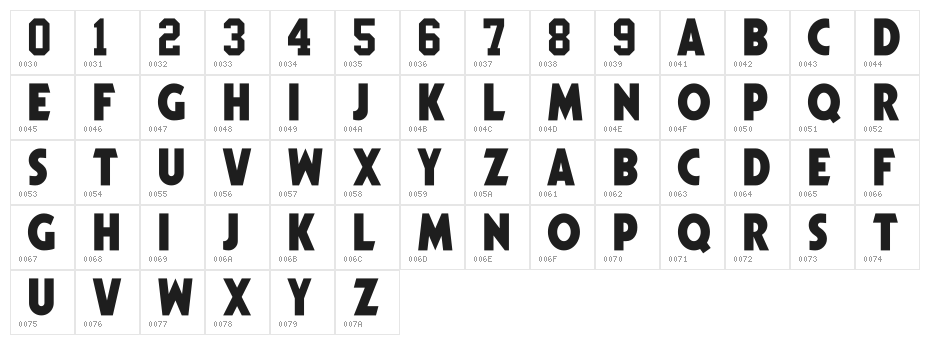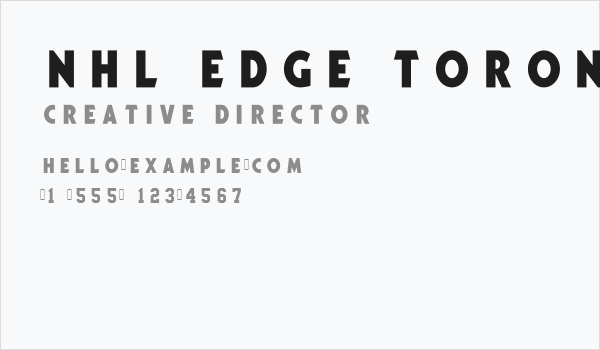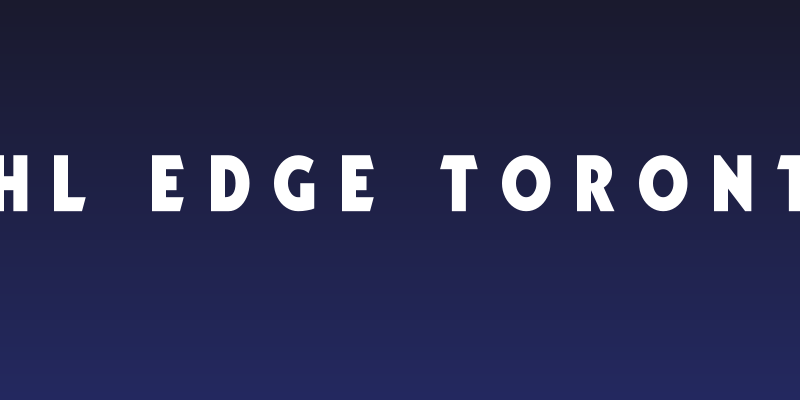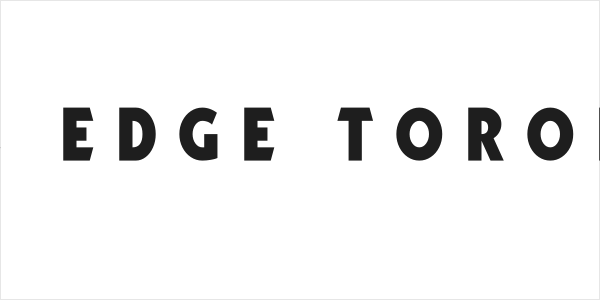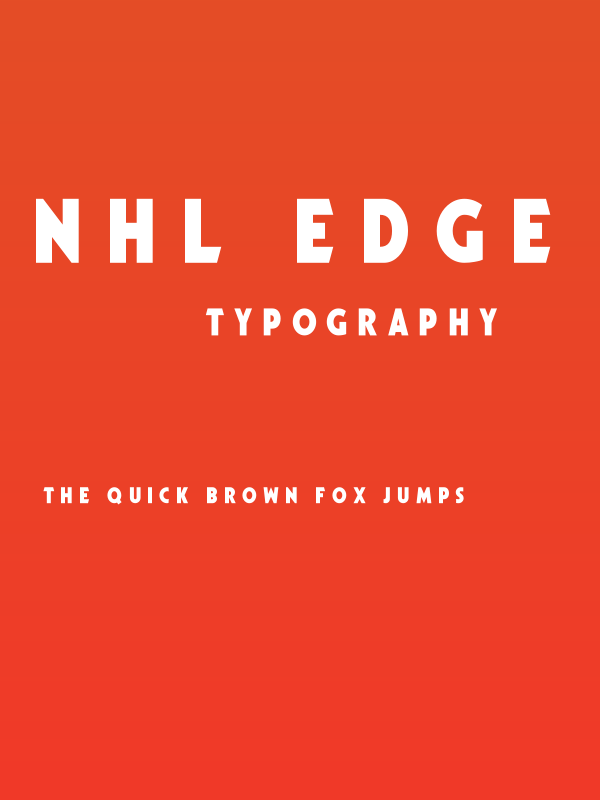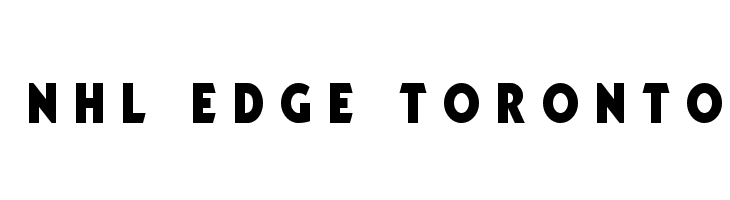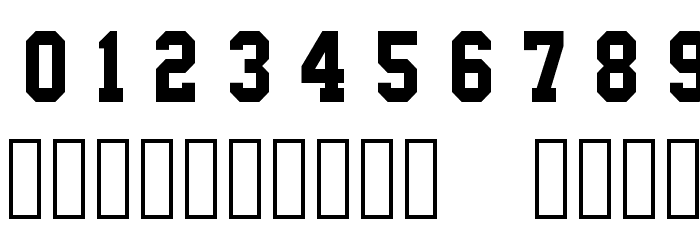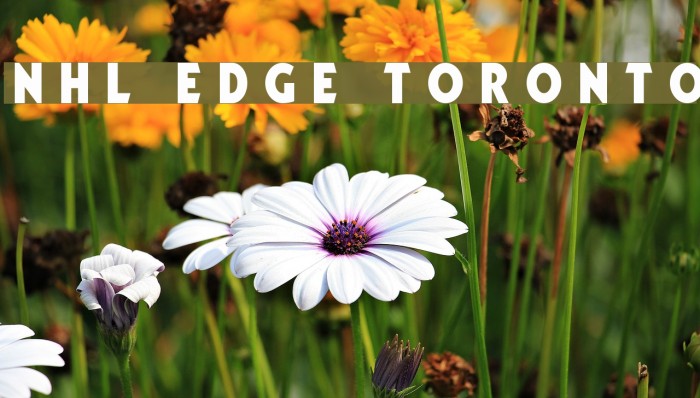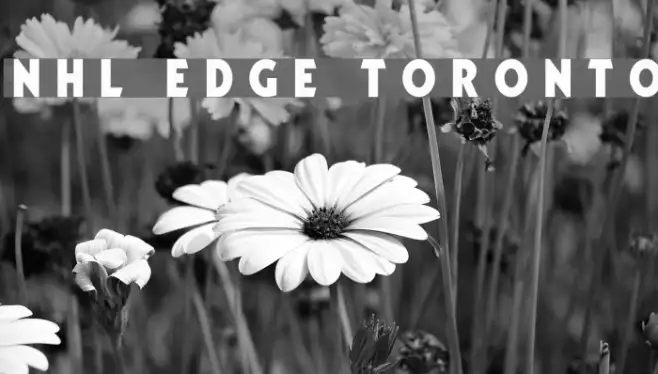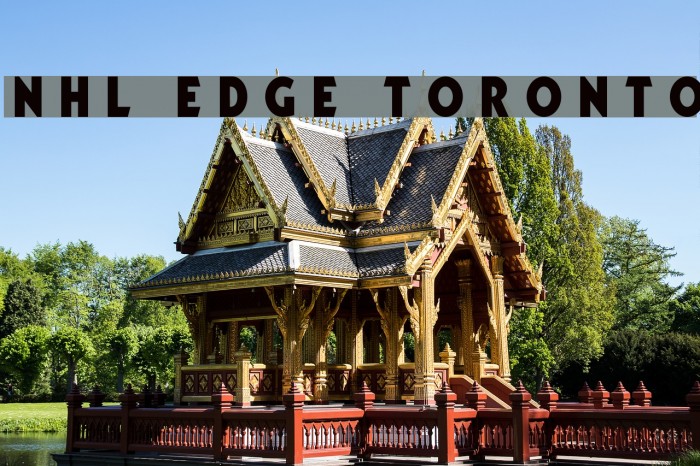
NHL Edge Toronto Font
| Caso d'uso | Logos, Headlines, Branding |
| Progetti proposti | Ideal for sports team branding, merchandise, posters, and any project requiring a bold, modern typeface. |